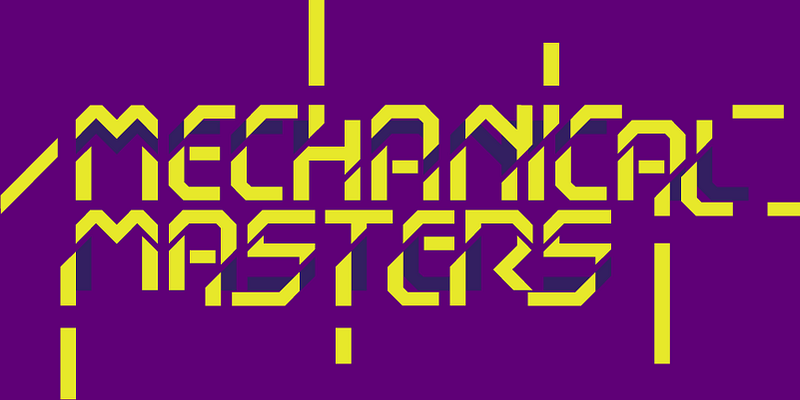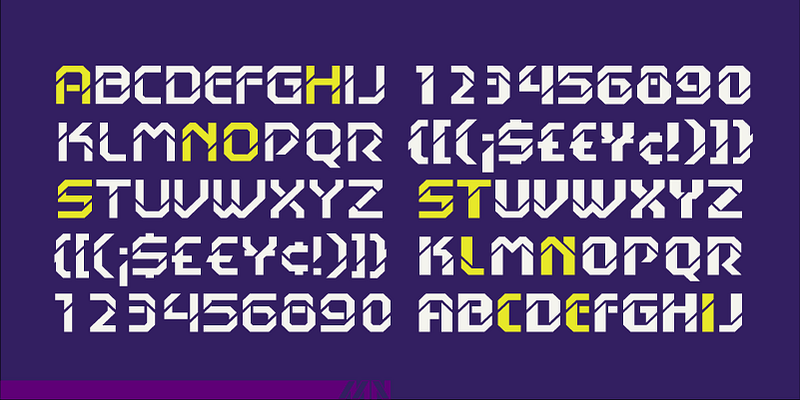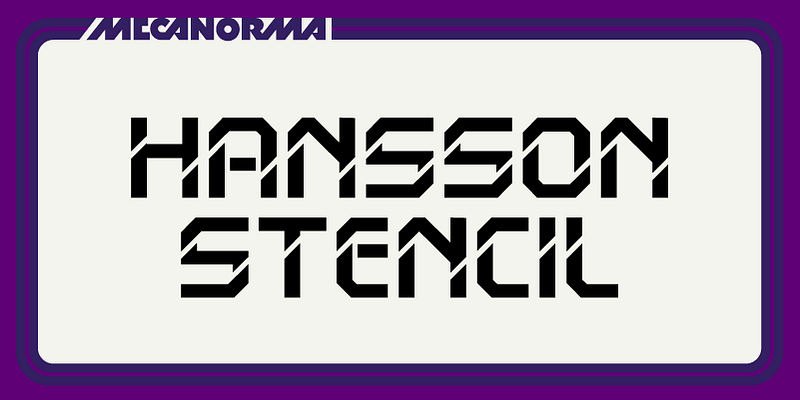
La empresa francesa Mecanorma ha sido uno de los principales proveedores mundiales de letras de frotado instantáneo. En 1995, Mecanorma se retiró del mercado de gráficos profesionales. Durante su tiempo en activo, sus productos de letras de frotado instantáneo se fabricaron en Trip Productions BV. En 2004, International TypeFounders (ITF) obtuvo la licencia de las tipografías digitales de Trip Productions BV y lanzó la cartera como Mecanorma Collection. De esta manera, se preservó una de las mejores bibliotecas de fuentes tipográficas de exhibición digitales que existen, combinando un arte y una artesanía auténticos con las herramientas de hoy en día. En 2014, ITF firmó un acuerdo permanente con los sucesores de Trip Production. Este acuerdo confirmó los derechos digitales exclusivos de ITF en todo el mundo sobre la colección.